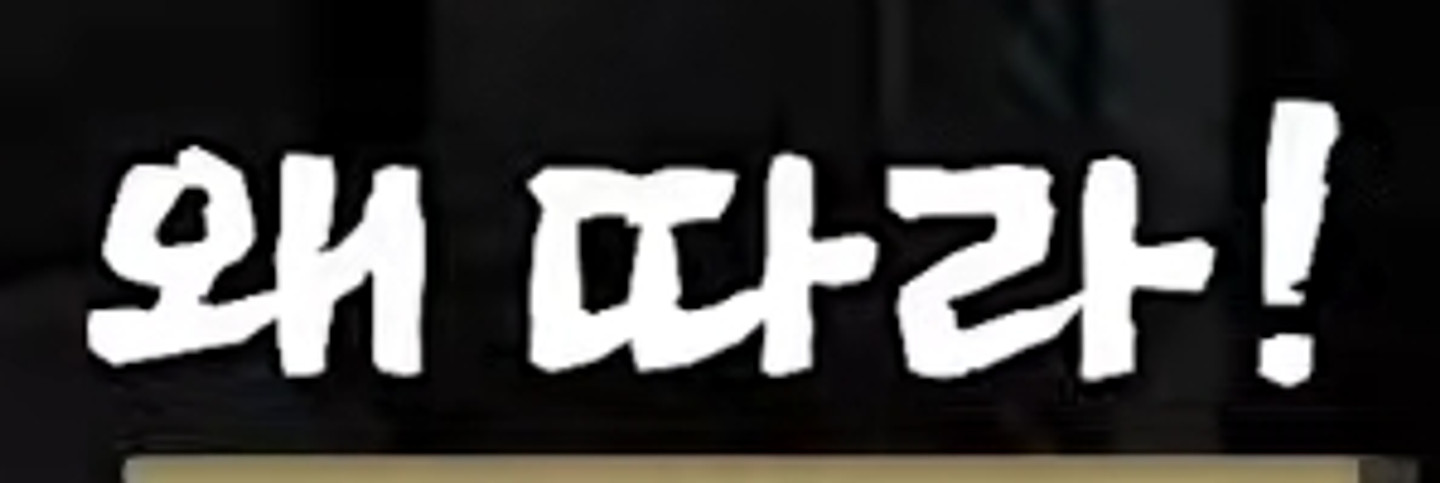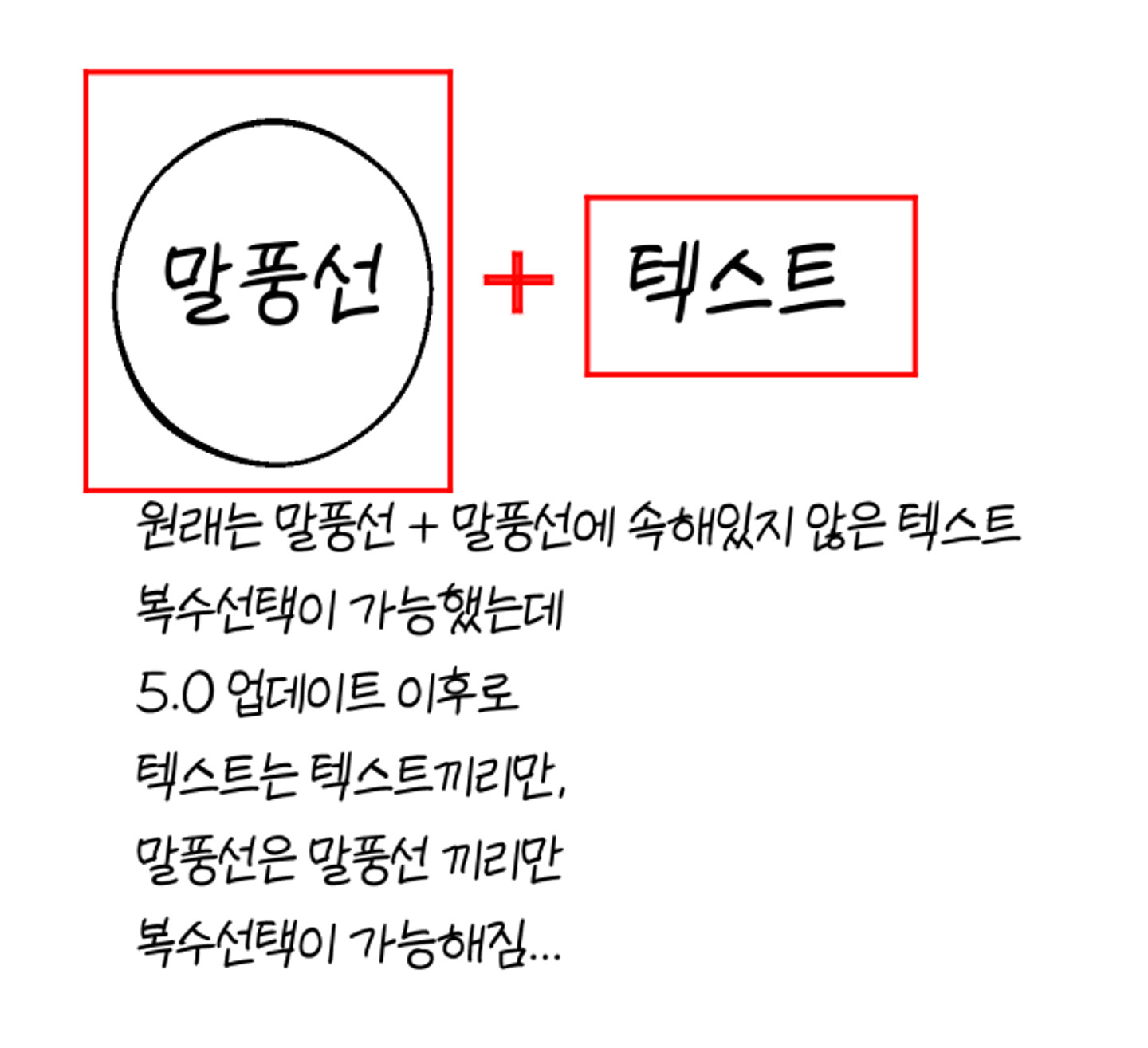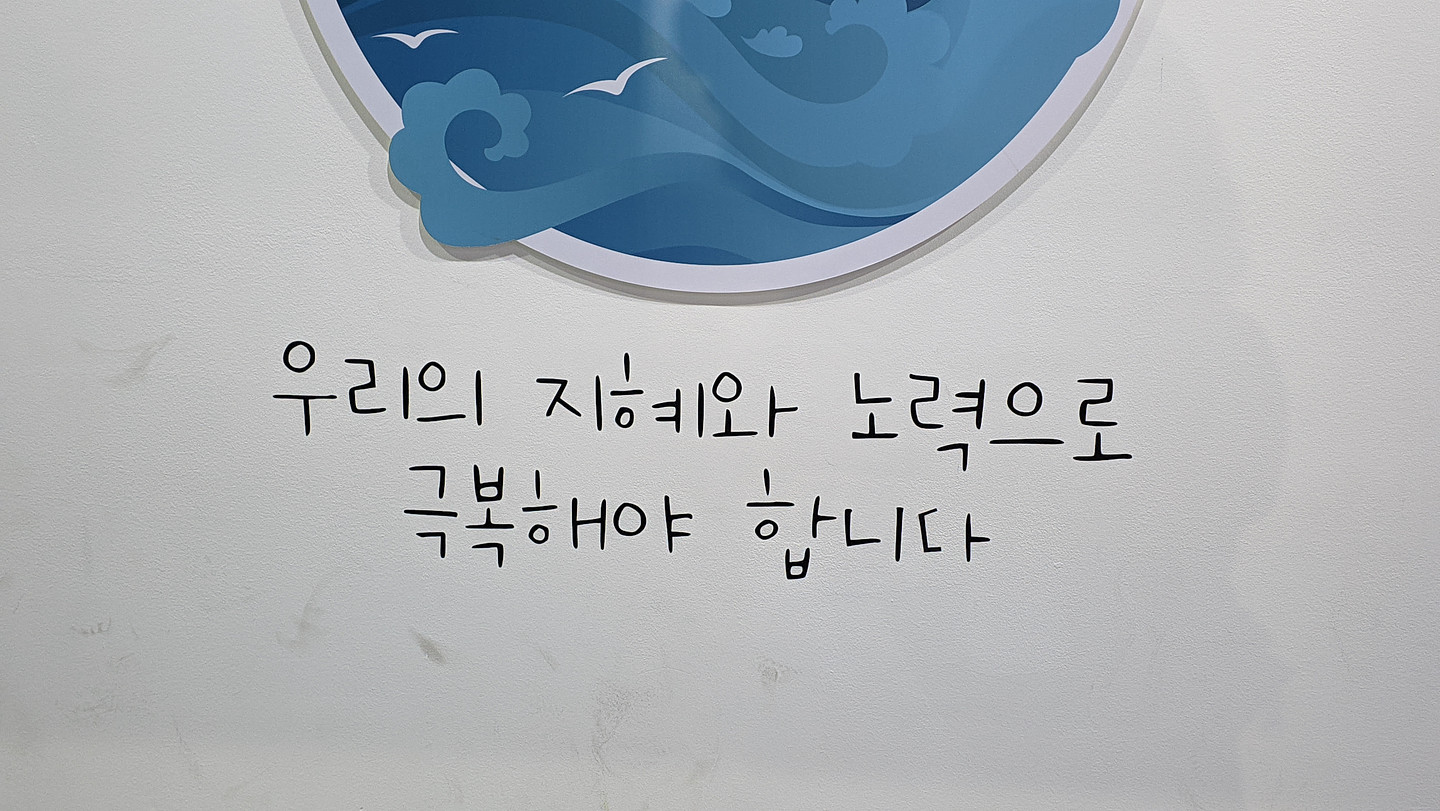
필기체 같은데?
이 폰트 어떤 폰트인지 아시는 분 계실까요~? 여러 폰트들을 봐도 애매하게 조금씩 다르네요
굴림체? 느낌인데 무슨 폰트인지 궁금합니다 ㅠㅠ
폰트가 궁금합니다.
무슨폰트일까요??
마플님 영상에 나오는 글꼴인데 아시는 분 있나요
요폰트가 뭘까요? 비슷한거라도 알려주셔요
일반 애플산돌고딕네오 는 아닌 거 같은데 궁금해요~
해당 폰트명이 궁금합니다. 이름 폰트와 & 기호 폰트 두 가지 모두 궁금해요
이거 무슨 폰트인가요ㅛ?
이거 글씨체 뭘까요ㅠㅠ
숫자 1 폰트가 먼가요? 중 반 글씨 폰트는 먼가요?